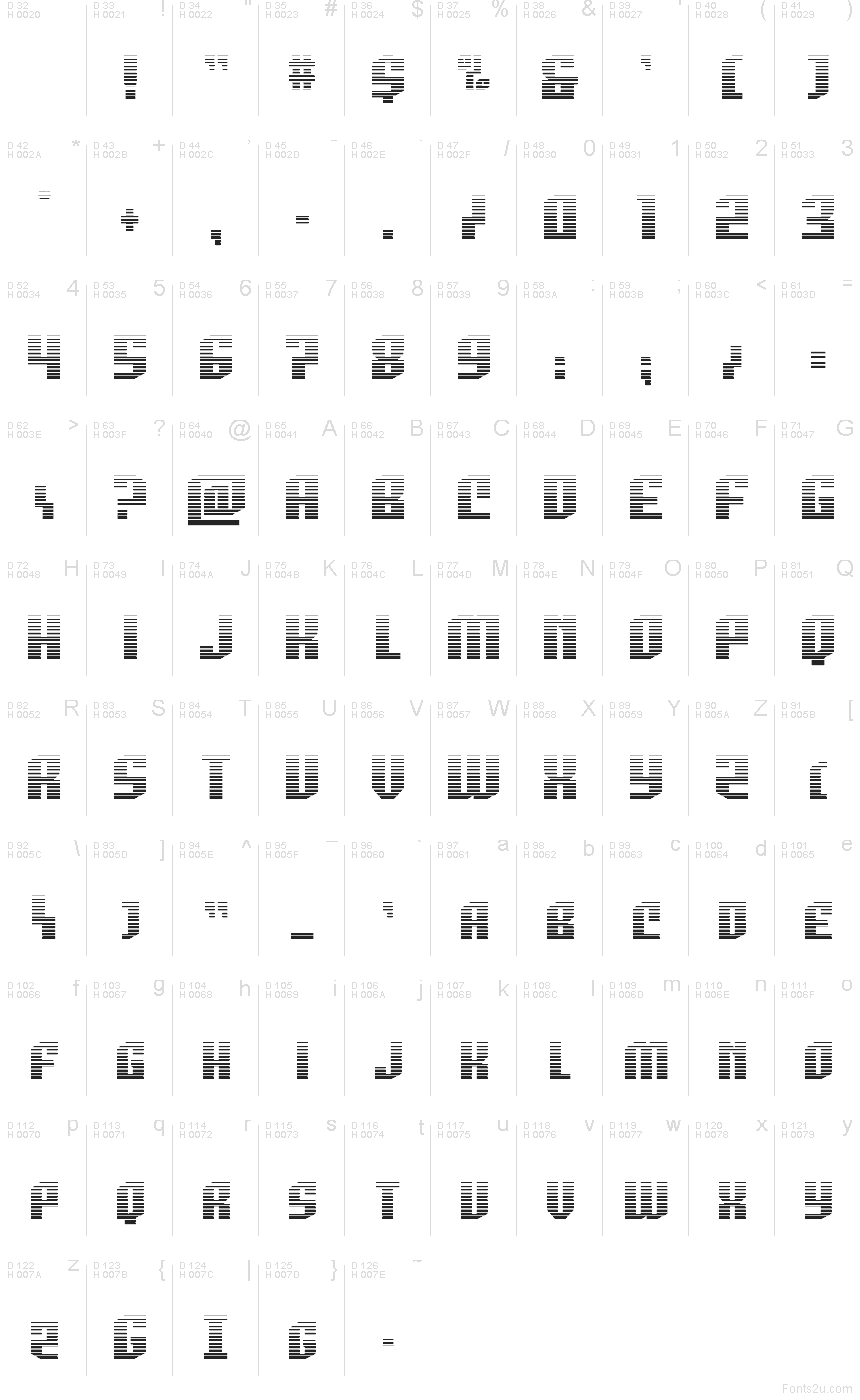
Viper Command Gradient od Daniela Zadorozny’ego z Iconian Fonts to darmowy font w stylu techno, którego znakiem rozpoznawczym jest wypełnienie w paski typu „scanline”, sprawiające wrażenie, jakby każde słowo pulsowało na ekranie monitora. Szerokie, kwadratowe formy i czyste odstępy zapewniają wyrazistość, a wbudowane pasy dodają ruchu bez potrzeby stosowania dodatkowych efektów – niczym cyfrowa przesłona przechodząca nad literami.
Viper Command Gradient świetnie prezentuje się na plakatach sci-fi, grafikach dla drużyn e-sportowych, nagłówkach interfejsów gier, nakładkach streamingowych, ulotkach wydarzeń technologicznych, opakowaniach gadżetów oraz futurystycznych projektach logo. Pozwól temu darmowemu krojowi pisma grać pierwsze skrzypce w dużych rozmiarach, a w tekście głównym zestaw go z prostą, geometryczną bezszeryfową czcionką, aby linie nie konkurowały ze sobą o uwagę.